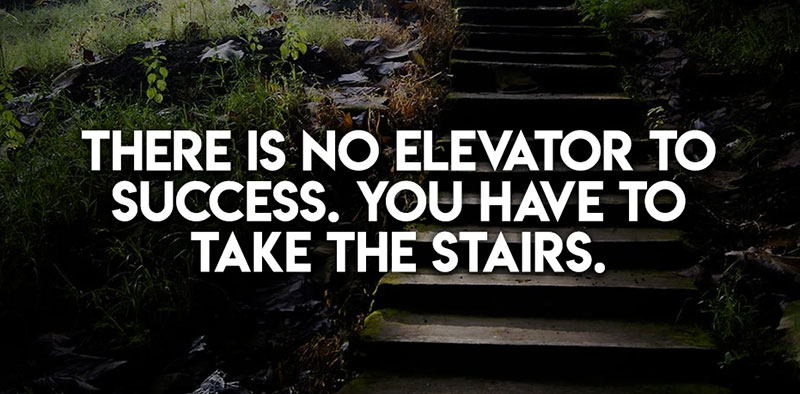
Haben Sie sich jemals gefragt, warum einige Zitate einfach im Gedächtnis bleiben? Es sind nicht nur die Worte; es ist die Schriftart, die Wirkung zeigt!
In der Welt des Webdesigns, in der ich täglich arbeite, kann die richtige Schriftart ein einfaches Zitat in ein unvergessliches Meisterwerk verwandeln.
Es geht hier nicht nur darum, Helvetica statt Times New Roman zu wählen; es geht darum, die Seele des Zitats zu verstehen und sie in ihr bestes Gewand zu kleiden.
In diesem Artikel führe ich Sie durch das Labyrinth der Serifen-, serifenlosen und Script-Schriftarten – jede mit ihrer eigenen Persönlichkeit, bereit, Ihren Zitaten eine Stimme zu geben.
Egal, ob Sie einen inspirierenden Social-Media-Beitrag erstellen oder eine kühne Marketingkampagne gestalten, die Kenntnis der besten Schriftarten für Zitate ist Ihre Geheimwaffe.
Wir erkunden alles von der Lesbarkeit von Garamond bis zur Eleganz von Barcelony Signature und sogar, wie das Schriftarten-Pairing Ihre Botschaft heben kann.
Top Inspirations-Schriftarten für Zitate
| Schriftartenname | Stil | Am besten geeignet für | Lesbarkeit | Besondere Merkmale |
|---|---|---|---|---|
| Beautiful Heart | Handgeschriebenes Script | Romantik/Inspiration | Hoch | Fließendes, elegantes Script mit Schwüngen |
| Savannah | Serif | Klassisch/Professionell | Sehr hoch | Traditioneller Look mit modernem Twist |
| Hallimun Signature | Script-Signatur | Persönliches Branding | Mittel | Natürliches handgeschriebenes Gefühl |
| September Twilight | Handgeschriebener Pinsel | Lässig/Künstlerisch | Mittel | Pinselähnliche Striche, lässig |
| Meticula | Serifenlos | Technisch/Zeitgenössisch | Sehr hoch | Klare Linien, geometrische Formen |
| Nesia Sans | Serifenlos | Modern/Unternehmen | Sehr hoch | Freundlicher, runder Charakter |
| Bison | Fett Serifenlos | Aussagekräftige Aussagen | Hoch | Stämmig und robust, auffällig |
| Hallelujah | Handgeschriebenes Script | Kreativ/Inspirierend | Mittel | Unregelmäßiger, spontaner Script-Stil |
| Army Buster | Slab Serif | Maskulin/Stark | Hoch | Militärinspiriert, solide Haltung |
| Madina | Script | Feminin/Dekorativ | Mittel | Fließende Linien, Pinselschrift |
| Barcelony Signature | Signature-Script | Persönlich/Intim | Mittel | Authentischer Signature-Look |
| Gelion Typeface | Serifenlos | Geschäft/Technisch | Sehr hoch | Modern, geometrisch serif… |
Folgen sind Bilder und thematische Informationen über Script- und Handschriftarten, seriflose und serifen-Schriftarten, einzigartige und thematische Schriftarten, fette und prägnante Schriftarten sowie elegante und raffinierte Schriftarten.
Spezialisierte Schriftarten für verschiedene Arten von Zitaten
Tatsächlich gilt für die besten Schriftarten für Zitate, dass eine Größe nicht alle passt. Wie, ernsthaft. Verschiedene Arten von Zitaten erfordern ihren eigenen einzigartigen Stil. Es geht darum, die Stimmung der Worte mit der perfekten Schriftart abzustimmen. Lassen Sie uns das aufschlüsseln.
Weitere Details und FAQs zur Schriftartenauswahl, praktische Tipps für Schriftartenkombinationen und Nutzung, sowie ein Abschluss, der die Bedeutung der richtigen Schriftartenauswahl betont.
Praktische Tipps zur Schriftartenkombination und -verwendung
Ausgleich von Schriftarten-Gewichten und -Stilen
Wenn Sie Zitate aufpeppen, denken Sie an die Schriftartenkombination wie an das Erstellen einer großartigen Playlist. Es geht um Harmonie und Kontrast. Die besten Schriftarten für Zitate auszuwählen bedeutet nicht nur, coole Schriftarten zu wählen; es geht darum, wie sie zusammenpassen.
- Kombination verschiedener Schriftartenarten: Mischen Sie beispielsweise Serif mit Serifenlos. Stellen Sie sich Helvetica (das ist Mr. Zuverlässig in der Welt der Schriftarten) mit etwas verspielterem wie September Twilight vor. Es ist, als würden sie direkt auf Ihrer Seite ein cooles Gespräch führen.
- Verwendung von Schriftgewichten zur Betonung: Spielen Sie mit fetten und leichten Gewichten. Angenommen, Sie haben ein Zitat. Der eindrucksvollste Teil? Machen Sie ihn fett. Der Rest? Halten Sie ihn leicht. Es ist, als würden Sie den besten Teil eines Songs hervorheben.
Berücksichtigung von Hintergrund und Farbe
Jetzt malen wir ein Bild. Die besten Schriftarten für Zitate benötigen den richtigen Hintergrund, um wirklich zu strahlen. Es ist, als würden Sie die Bühne für Ihre Worte bereiten.
- Schriftfarbwahl: Farben sprechen, wissen Sie. Ein weißer Schriftzug auf dunklem Hintergrund für etwas Tiefgründiges. Leuchtende Farben für etwas Fröhliches. Es ist, als würden Ihre Schriftarten Stimmungsringe tragen.
- Kompatibilität mit dem Hintergrund: Der Hintergrund ist Ihre Leinwand. Einfach oder texturiert? Stellen Sie sicher, dass Ihre Schriftarten nicht verloren gehen. Es ist wie das Finden der perfekten Beleuchtung für ein Foto.
Häufig gestellte Fragen zu den besten Schriftarten für Zitate
Was macht eine Schriftart großartig für Zitate?